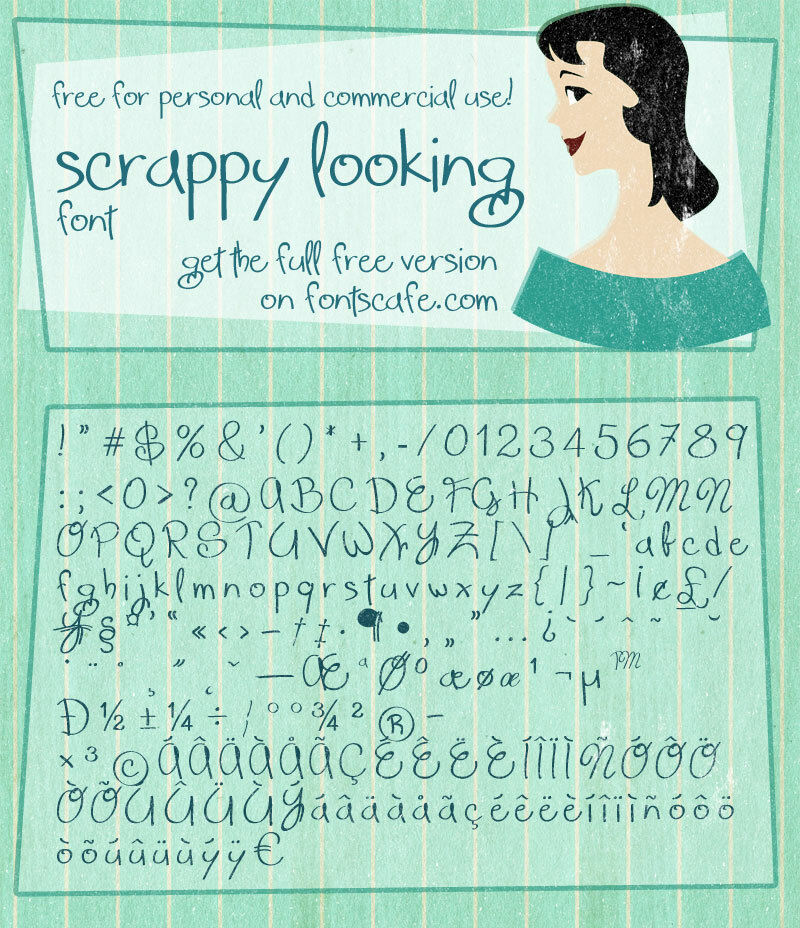
Scrappy Looking, ein einzigartiger Entwurf von fontscafe.com, besticht durch sein leichtes Gewicht und seinen handschriftlichen Stil, der eine ungezwungene und sympathische Note vermittelt. Diese Schrift fängt die Essenz spontaner Handschrift ein und ist damit perfekt für Projekte, die eine persönliche Note mit einer Prise Verspieltheit erfordern. Ihre fließenden Linien und die organische Form bieten eine Ästhetik, die gleichzeitig charmant und nahbar wirkt.
Die Scrappy Looking ist vielseitig genug, um allem von Grußkarten bis hin zu Branding-Materialien Charakter zu verleihen, wo Authentizität und Kreativität im Vordergrund stehen. Ihr unverwechselbarer Stil eignet sich besonders für Designs, die informell und dennoch einprägsam sein sollen. Ob Sie Einladungen gestalten, Boutique-Verpackungen entwerfen oder die Typografie Ihres Blogs individualisieren – Scrappy Looking bringt ein Element handgefertigter Unvollkommenheit ein, das jedes Projekt sofort persönlicher und ansprechender wirken lässt.